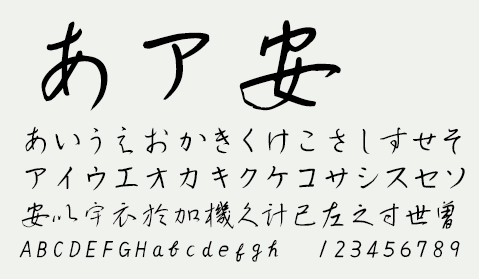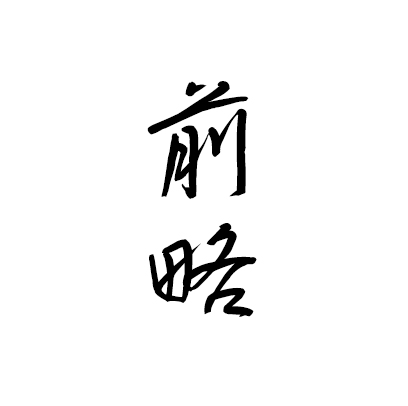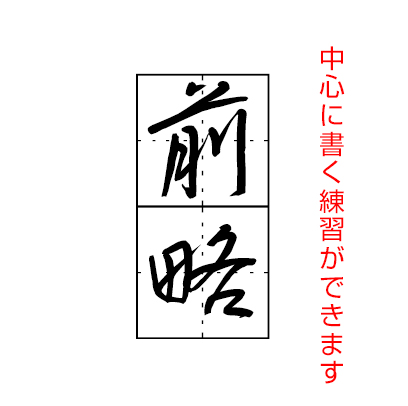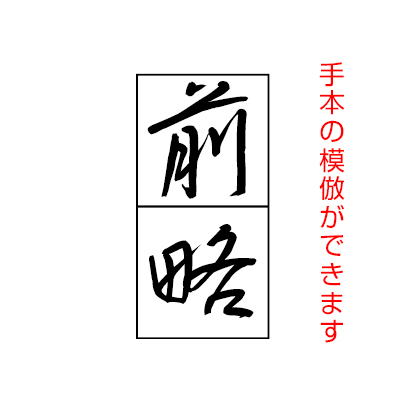
アンバランスな空間の美しさを残しながら、
自然な手書き風の文字形に仕上げました
ウェイト見本
- NSK白洲ペン字行草フォント/w1
- NSK白洲ペン字行草フォント/w3
- NSK白洲ペン字行草フォント/w6>
NSK白洲ペン字行草手本セット
フォント別特徴
ひらがな・カタカナ・漢字を使い分けることで、より美しい文字バランスを実現できます
| NSK⽩洲ペン字行草フォント (標準形) |
升目付き | 外枠付き |
学びたい文字を入力・印刷するだけでオリジナルのペン字手本を作成できます